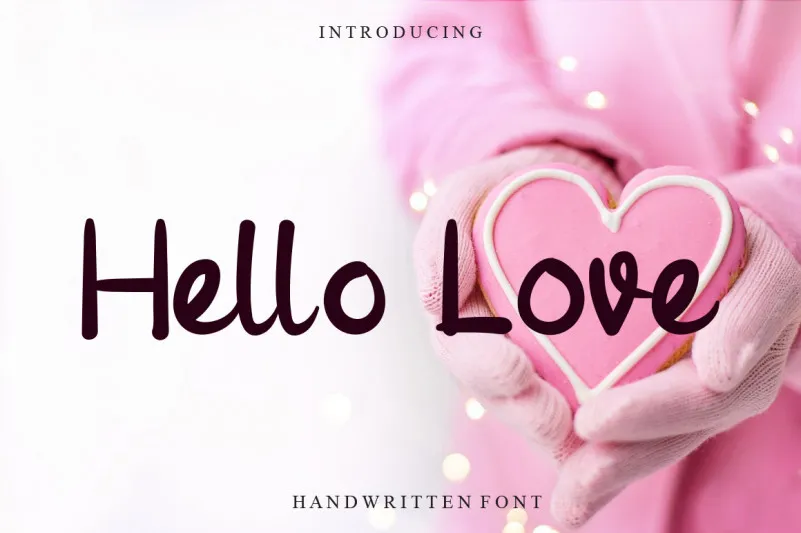
Hello Love Font – Fonte Grátis
Hello Love Font
A ‘Hello Love Font’ é uma elegante escolha para quem busca um toque encantador em seus projetos digitais. Com seu estilo retrô e alegre, essa script font retrata um amor incondicional que faz a diferença no design das suas campanhas ou logotipos. Perfeita para dar um tom de aconchego e carinho ao seu trabalho, ela se destaca como uma opção criativa e divertida para qualquer tipo de criação visual. Seja para criar o nome do seu negócio, adicionar um toque personalizado aos seus materiais de marketing ou mesmo decorar textos informativos, essa fonte é perfeita para aqueles que desejam transmitir um sentimento de carinho e amizade em suas obras.